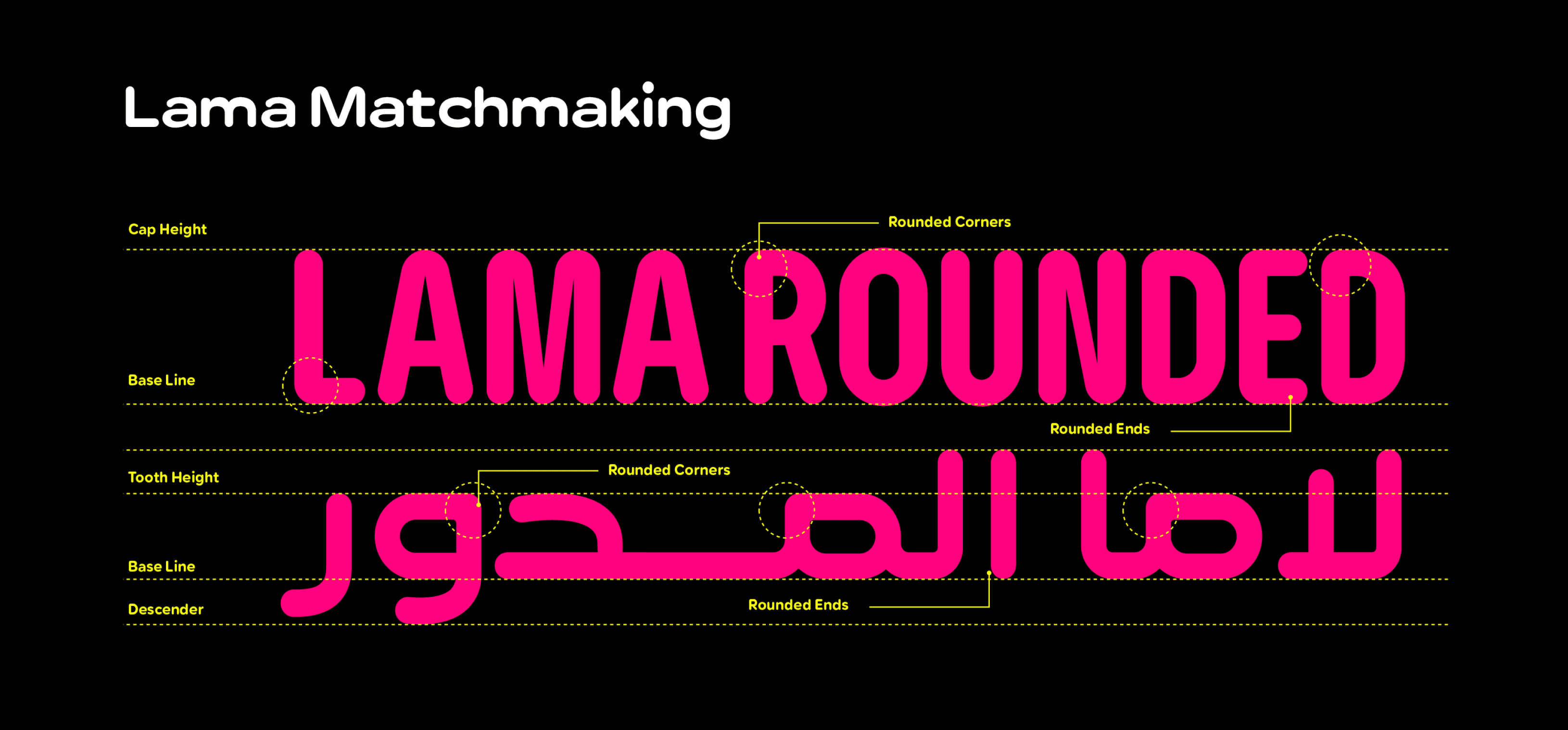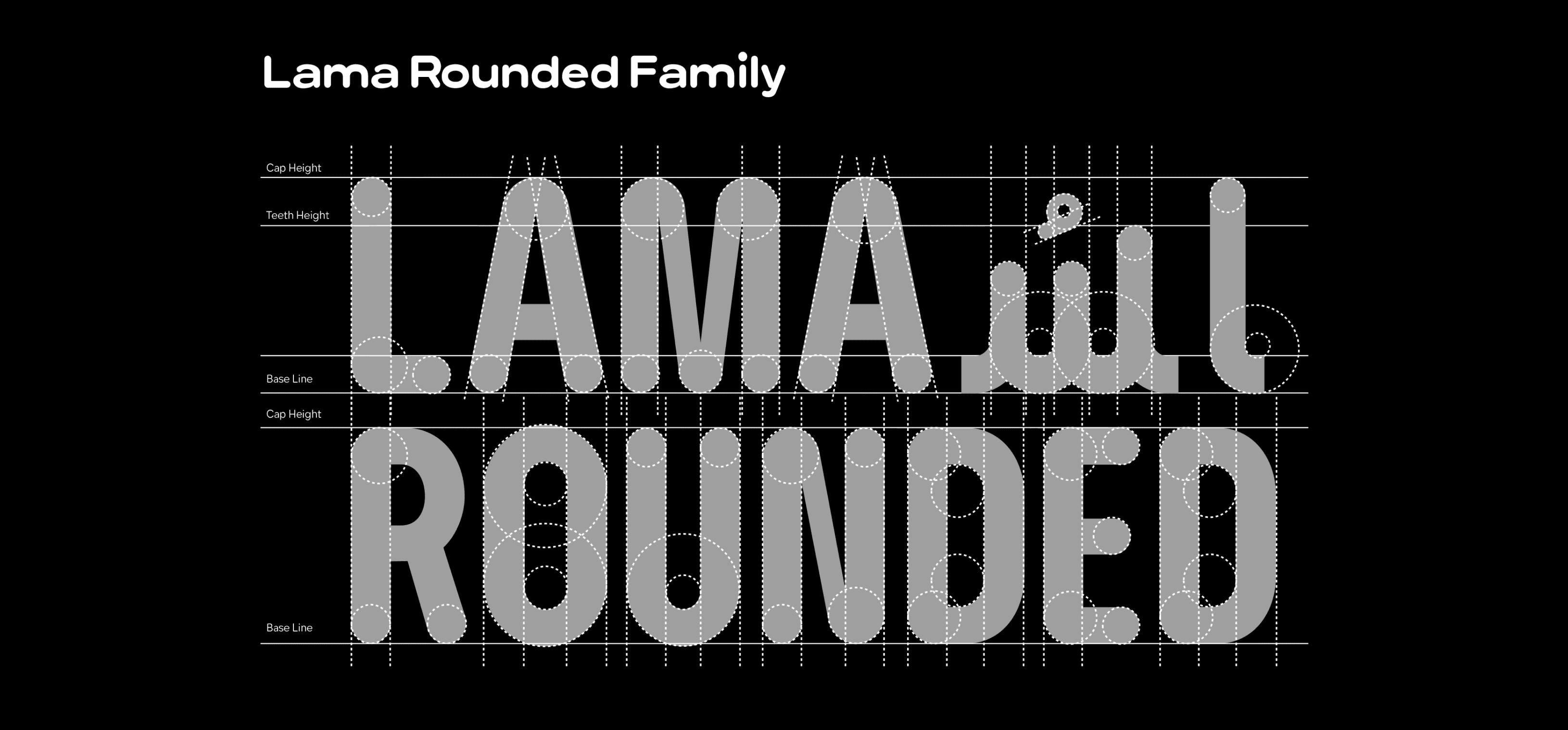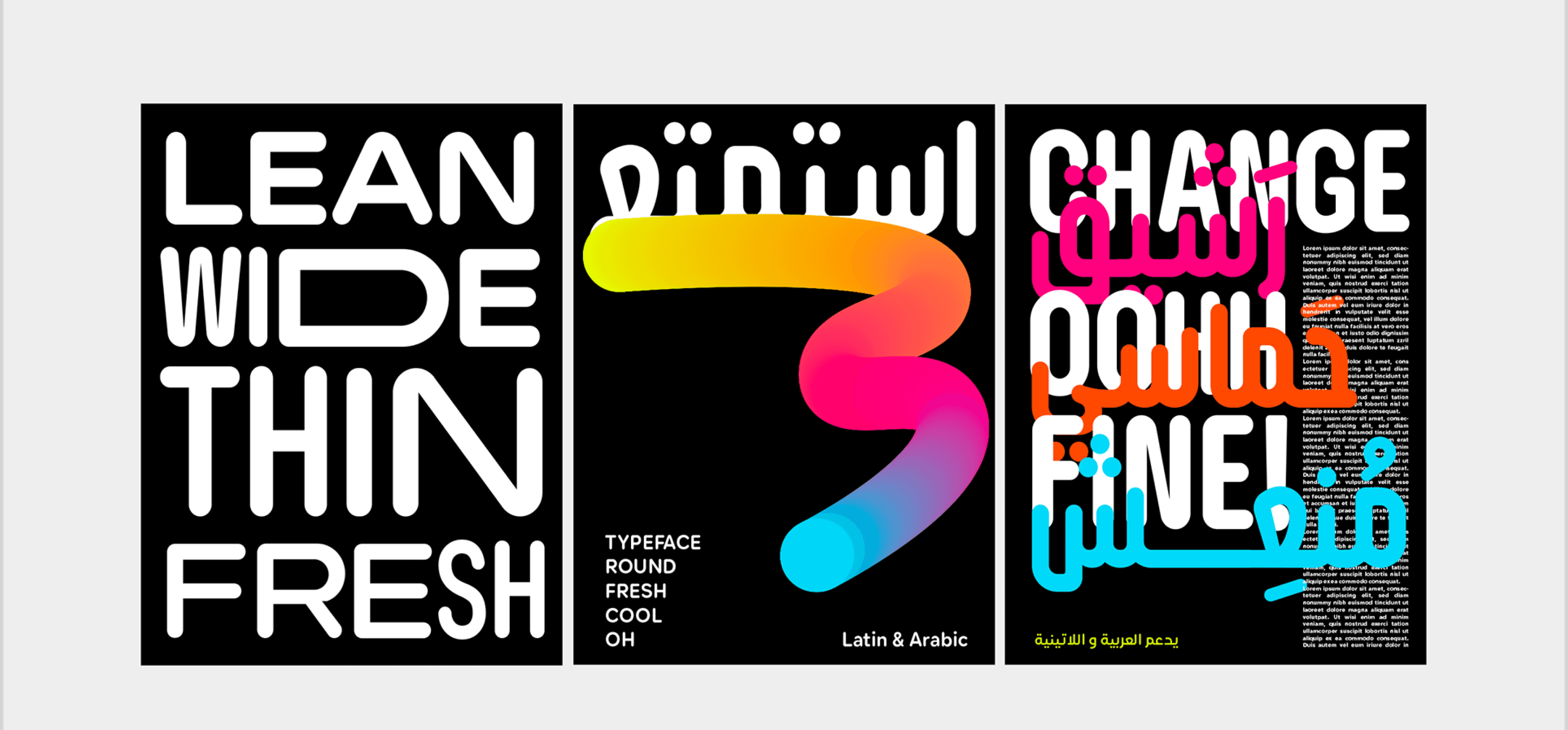
لاما راوندد هو امتداد لعائلة خطوط لاما سانس. وقد استُلهمت عملية تصميمه من الحاجة إلى إنشاء خط دائري لا يعطي انطباعًا طفوليًا ويظل عمليًا في المساحات الصغيرة.
بالنسبة للإصدار اللاتيني، اعتمدنا على الأساليب القديمة للخطوط اللاتينية الجروتسكية والدائرية. أما في النسخة العربية، فكان الخط الكوفي هو مصدر الإلهام. وقد أسفر دمج كلا الأسلوبين عن نظام طباعي متكامل.